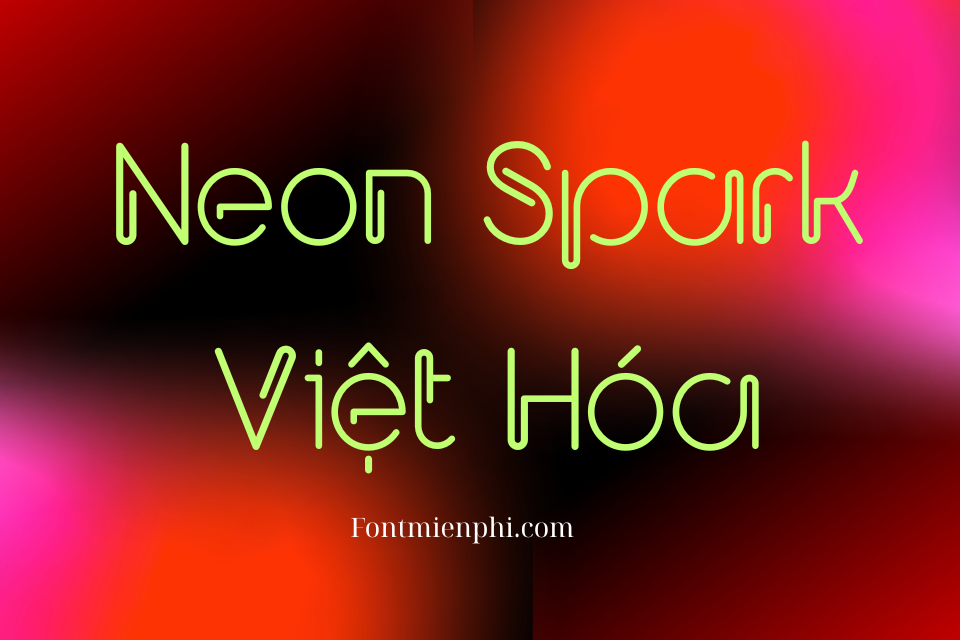
Font Việt hóa 1FTV VIP Neon Spark
Font 1FTV VIP Neon Spark là một kiểu chữ phong cách neon, mang đến cảm giác hiện đại và nổi bật. Dưới đây là một số đặc điểm nổi bật của font này:
• Thiết kế chữ: Font này có các nét chữ mảnh mai, sáng bóng, thường được sử dụng trong các thiết kế liên quan đến ánh sáng và không gian đêm.
• Phong cách: Được lấy cảm hứng từ ánh đèn neon, font này thường có độ sáng và sự lấp lánh, tạo cảm giác thu hút và sinh động.
• Ứng dụng: Thích hợp cho các dự án thiết kế đồ họa, quảng cáo, hoặc bất kỳ sản phẩm nào cần tạo điểm nhấn mạnh mẽ và sự trẻ trung.
• Hỗ trợ tiếng Việt: Font này được thiết kế để hỗ trợ đầy đủ các ký tự tiếng Việt, giúp người dùng dễ dàng sử dụng trong các văn bản tiếng Việt mà không gặp phải vấn đề về hiển thị.
Ngoài ra, 1FTV VIP Neon Spark có thể được sử dụng trong nhiều lĩnh vực khác nhau như thời trang, âm nhạc, và sự kiện, nơi mà sự nổi bật và tính thời thượng là điều quan trọng.